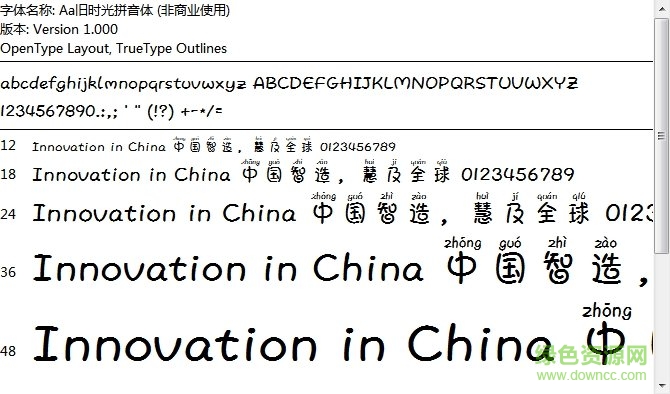
舊時(shí)光拼音體ttf是aa字體管家推出的一款非商業(yè)使用字體,字跡圓潤(rùn)活潑,很有卡通字體的可愛(ài)和生動(dòng),讓你的文字閱讀更加舒適怡然,喜歡的朋友就來(lái)綠色資源網(wǎng)下載收藏吧!
P.S.拼音字體存在多音字拼寫錯(cuò)誤的問(wèn)題,多音字以常用音調(diào)為準(zhǔn)。
拼音字體都有相同的特色就是清晰醒目的拼音注釋,便于兒童對(duì)漫畫圖書內(nèi)容的獨(dú)立閱讀,也讓我們更好的讀書看報(bào),而中英文的特色也決定了該字體的使用風(fēng)格,舊時(shí)光拼音體偏向于pop字體,用于海報(bào)創(chuàng)意或與兒童相關(guān)內(nèi)容的設(shè)計(jì),效果更佳突出!